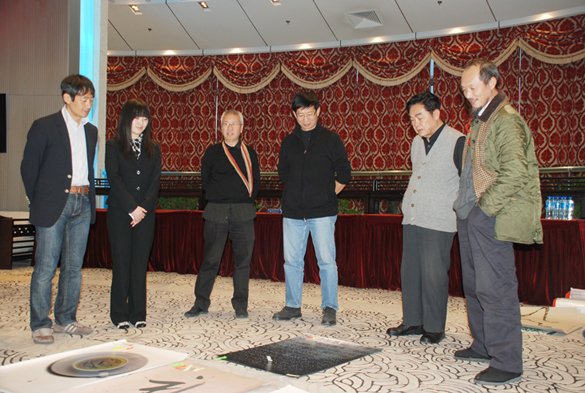
第四届“方正奖”中文字体及海报设计大赛获奖作品揭晓
2007年12月16日,备受各界关注的第四届“方正奖”中文字体及海报设计大赛评审工作如期在方正大厦拉开了帷幕。
评委们评审中文字体设计最终获奖作品
评委们评审海报设计最终获奖作品
“方正奖”中文字体设计大赛旨在将古老的汉字文化与现代设计理念、手法相结合,以促进中文字体的创新,丰富中文字体的种类。自2001年6月举办以来,至今已成功举办了三届,第四届“方正奖”中文字体及海报设计大赛与以往相比增加了两项内容:在中文字体设计类中增加了“书法中文字体设计”,意在将中国古代书法如“颜、柳、欧、赵”等书法艺术融合到现代艺术中,并适合印刷、网站、电视、手机等使用;同时增加了以汉字为主题的海报设计,参赛者以海报的形式展现汉字的魅力。
此次大赛得到了国内外字体设计爱好者的热烈响应,至截稿日期为止,组委会共收到来自世界各地参赛者的2000多件作品。大赛组委会邀请了莱诺泰普字体指导小林章先生、中央美术学院设计学院院长王敏教授、北大方正电子有限公司(以下简称“方正电子”)字体设计总监朱志伟先生、中央美术学院吕胜中教授、中央美术学院李少波先生、原清华大学美术学院资深教授余秉楠教授、香港著名设计师靳埭强先生及旅美著名艺术家徐冰先生等八位著名字体和艺术界权威人士担任评委,就参赛作品的创意、字体结构、字形规范等方面进行了评分。
一等奖
韦薇——月光体
创作意图:本字体由虚渐入实,生动且富有灵性。大方得体,赏心悦目,如月光倾洒,恬静而不失典雅。
专家点评:靳埭强:这款字体折纸光影的原理,利用垂直、水平与斜线,深浅、明暗的不规则弧度,营造有个性和趣味的富创造性的字体,值得奖励。
余秉楠:由虚入实,恬静而动。如月光倾泻神州,尽得诗情画意。
小林章Akira Kobayashi:A very unusual and interesting approach to designing a typeface. Amazing it looks also good in photocopy! A fun to look at!
李少波:这是一款极具魅力的字体作品。当我站在它面前时,仿佛就入到了一个静寂的夜晚。月光透过窗棂门隙洒落到地面,窗外松风瑟瑟,屋内字影婆娑...... 倾刻间,这副美妙的图景将字体的具体功能消解覆盖。汉字——这门古老文字的独有魅力再次得以呈现。
朱志伟:用现代手法将浓淡虚实的意境融入字体中,笔画间的取舍和借让表现出作者对汉字字型的把握独具匠心,个别字虽不易辨认,但稍加品味即可认出,顷刻间会平添几分意趣。
徐冰:作者的想象力超越于一般字体设计的范围,灵感来自于屏幕时代的特殊经验。
二等奖
葛玉泉——新颜体
创作意图:在颜体结构基础上将笔画重新整合归纳,简化横、竖,强调钩、捺,在传统书法中融入简洁利落的现代审美意趣,使字体端秀舒展、清新挺拔。
专家点评:靳埭强:以传统书法名家风格,设计成个性强,而具现代感的新字体,显出设计者对传统的消化承传,而能加入自我的思维与创新,可喜可贺也。
余秉楠:简化了横、竖,强调了钩、捺,整合归纳使旧颜复新貌,赋予了现代意识。
李少波:作者将颜体字的笔画直接与几何化的笔形组合在一起,形成巨大的反差。听起来似乎是很危险的手法,然而,最终的效果却让人觉得震撼而有趣。作品的成功首先受益于“颜体”本身的巨大魅力。
朱志伟:成功的将颜体神韵与现代字体结合在一起,即传统又时尚。结构宽博严谨,笔画设计灵动自然,是一款即具艺术性又有实用性的好字体。
徐冰:能感受到设计者对汉字结构的认知与现代字体设计之间的关系。
高斐——鸿雁体
创作意图:该字体设计吸收了传统鸟篆的造型特点。鸟篆是篆书的一种,其笔画由鸟形替代,不仅装饰风格独特,更有深刻的象征意义。以飞鸟入书表达了中国古人所推崇的一种为人之道,候鸟守冬去春来之信,“信”是鸟篆的意义所在。鸟不仅代表守信的人格,也是信息传递迅速的象征,自古有“鸿雁传书”之说,字与鸟同飞当然可以更快的将信息带往遥远的地方。
传统篆书笔画多,结构复杂,现在大多数人对其已较感陌生,很多文字不易辨识。“鸿雁体”在设计时对文字结构尽量简化,笔画造型更多吸收了篆书均圆柔婉的风格,表现出鸿雁的飞翔之势,而不出现具体的鸟形,一方面是出于文字整体感的考虑,另一方面也是想取得一种境界,将想象的空间留给观者。
专家点评:靳埭强:作者能准确掌握鸟篆的笔画特点,又将现代造型简洁的手法设计此“鸿雁体”。优美易认,结构完善,是承传创新的经典佳作。
余秉楠:如雁飞翔,飞翔不见雁。如篆古朴,古朴却新颖。给人留下了丰富的想象空间。
小林章Akira Kobayashi:A good harmony of traditional letterform and modern design! Great!
李少波:该字字形优美,趣味生动。特别是对于笔画和结构的处理,大胆而周详。如单人旁较忠实的保持篆体风格,诸如此类的细节关照使得这件充满现代气息的作品古意盎然。
朱志伟:赋予小篆新的生命,每一笔画都犹如一个运动着的生命,积极向上,永往直前。
徐冰:一种极美的流动感和整齐感,用新的方法,将中国的书法的“现场感”,显现在现代字体设计中。
三等奖
陈三洪——丽宋
创作意图:宋体是一种内容丰富的字体,时而严肃,时而庄重,时而古朴,时而美丽。
专家点评:靳埭强:此宋体清丽秀健,外柔内刚,神气均备,独特而优美,不可多得的佳作也。
余秉楠:纤秀典雅,婀娜多姿,读来赏心悦目,如沐春雨。
李少波:精细的笔画设计给这款字带来了独特的性格,宋体字的特点在这里被悄悄的改变着,一些更为自然的细节像是从字中“生长”出来的幼芽、茎蔓,或是叶尖上掉下的水珠,构成这幅作品中最人性化的美学特征。
朱志伟:就宋体而言,具有突破性的创新,除了横轻竖重外,已经没有多少宋体字的特征,但在视觉上它具有同宋体字一样的阅读适性。宋体字的特征是工具使然的结果,而丽宋的笔形设计,正是消除了这种工具的痕迹。
徐冰:同意作者的自我阐释:“时而严肃,时而庄重,时而古朴,时而美丽”。
原创书写:施子欣 字型制作:黄陈列——新正楷
创作意图:书写者,以其逾半世纪精研欧阳询法书之深厚功底,设计创造出这一结体清闲端劲,笔势酣畅灵动之书体,具优雅、易识、易读等特质。用途广泛适用于教科书、应用文、书法教材、诗文、书报、广告、杂志之内文印刷。
专家点评:靳埭强:设计者能研习楷体写出独具风格的新体,显出个人的功力,这“新正楷”端正而不平板,内蕴高雅气质,气韵生动。
小林章Akira Kobayashi:A well-balanced and extremely readable type font. Every letterform is beautiful. Pleasing to look at.
李少波:这是一款实用性很强的作品,整幅字特征统一,笔形优雅,再现了楷字神韵。另外由于空间结构处理严谨,使得这款字在排版中尤胜一筹。
朱志伟:新正楷表现出作者的书法功底深厚,结字布局的技法娴熟,但看排版小样,个别字的体式还不够协调,缺乏整齐流畅的行气。 书法作品主要用于欣赏,印刷字体主要用于阅读,二者虽同出一源,却有很大的区别,印刷字体比书法作品有着更严格的要求,作为楷书的印刷字体要求结体取势统一一致,字与字间距合理,平稳流畅,行气贯通。
徐冰:一种很内敛的字体,正文小号字更精彩。
颜小武——颜氏宋体
创作意图:承颜体筋骨风格;见古典雍容大气;张厚重拙直一侧;弛仿生曲线对边;创鹅头鱼肚新意;之外圆内方规则;犹着力健儿壮美;似矍铄老者端庄。
专家点评:靳埭强:这款粗宋字体具传统古风而具现代美感,壮美厚重,视觉冲击力强,佳作也。
李少波:这是一款结合了“美术字”与“书法字”特征的作品。美术字设计的生趣与颜体的气度被天衣无缝地融合在一起。虽然在“竖勾”笔画的处理上略显局促,但瑕不掩玉,这仍是一款难得的上乘之作。尤其是作者的创作手法值得推崇。
朱志伟:有一种厚重的历史感,能联想到古代衙府的匾额对联,大跃进及文革时期的标语口号,也能感受到颜体影响的深远与广泛。 该字体端庄雄伟,肃穆中有几分灵动,适用于广告及包装设计。
评审委员奖
徐冰:梁天爽——维体
创作意图:人的视觉会对离得更远的东西尤其感兴趣,因为那种神秘感,我们掉入了漩涡,找不到最里面的是什么,当你抽身事外,你会看到一个似乎朦胧的印象。选用经典的宋体来表达这一主题,希望字体最后能够回归平淡,剥离幻象。
专家点评:徐冰:在我个人的以往的关于书体、字型设计的经验中,“维体”给我一种对汉字少有的,如此特殊而精彩的感受,这种感觉在数码技术出现之前是不可能有的。有意思的是,它又给人一种古老的民间鸟字画的感觉。这是一种神奇的“概念字体”,它把这件事带入到一个新的维度中。
靳埭强:徐艺玲——胶布字
创作意图:尝试用一种新的方法创造新字体,先把文字用字库里原有的字体方正大黑简体打印出来,然后拿胶布把文字进行有意识的削减。所以我所说的胶布字并不是用胶布做成,而是胶布是字构成的一种工具。在此实验过程中,一直很期待地想知道这些字在电脑加工后的感觉会是怎样。在这个电脑的时代,我们应更多地用手去解决问题。
专家点评:靳埭强:设计者能运用一种很普通的用具化为设计工具,有大胆实验创新的思维,在高科技时代能回归到心手合一的本位,难能可贵。以此创新手法,设计出拙朴而感性,具自然天趣的字体。
小林章Akira Kobayashi:A very unusual approach, but the balance of balck-and-white was extremely well made. A fun to look at !
朱志伟:唐一鸣——提行
创作意图:印刷正文字体行书的种类相对偏少,猜想是因为行书的笔画不易规范,识读也不如正楷类清晰,正规的文字场合更是很少使用“行书”。但古人的书道心思放在“行书”的居多,所以也尝试制作了一套“行书”。
专家点评:朱志伟:此字体是启功书体与瘦金书的巧妙结合,字形结体坚净儒雅,笔画起始及转折清劲瘦硬,映带顾盼之姿,气贯意连,颇具实用性。个别字笔画轻重对比关系可进一步斟酌,如“有”字的“月”,“者”字的“日”如调整为左轻右重可能更为理想。
李少波:作品仿瘦金体风韵,既保持了原字中潇洒利落的笔画特征,又作了新的创造,例如在“若”、“有”字中强调的连笔处理,使得这款字性格得以凸显。
余秉楠:尹玉婷——矛盾体
专家点评:小林章Akira Kobayashi:The idea of creating a joining script typeface may not be new, but it’s extremely difficult to do it well! This font has a flow and every character is well-balanced.